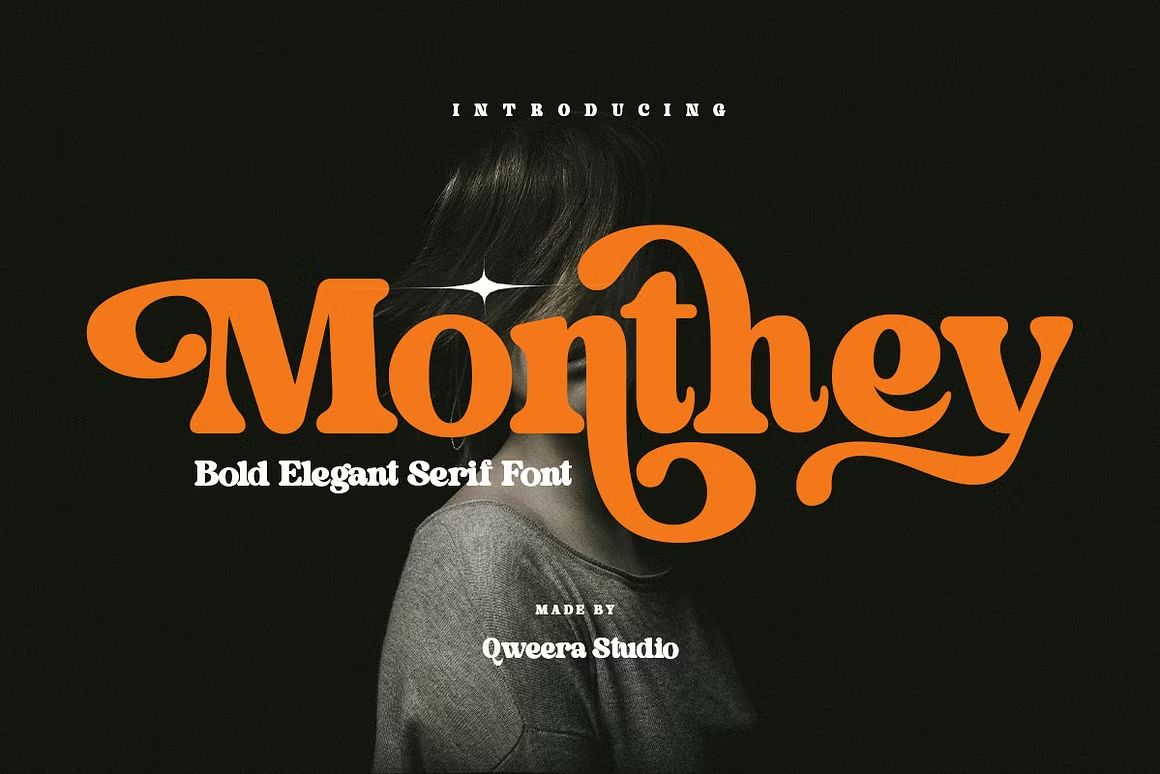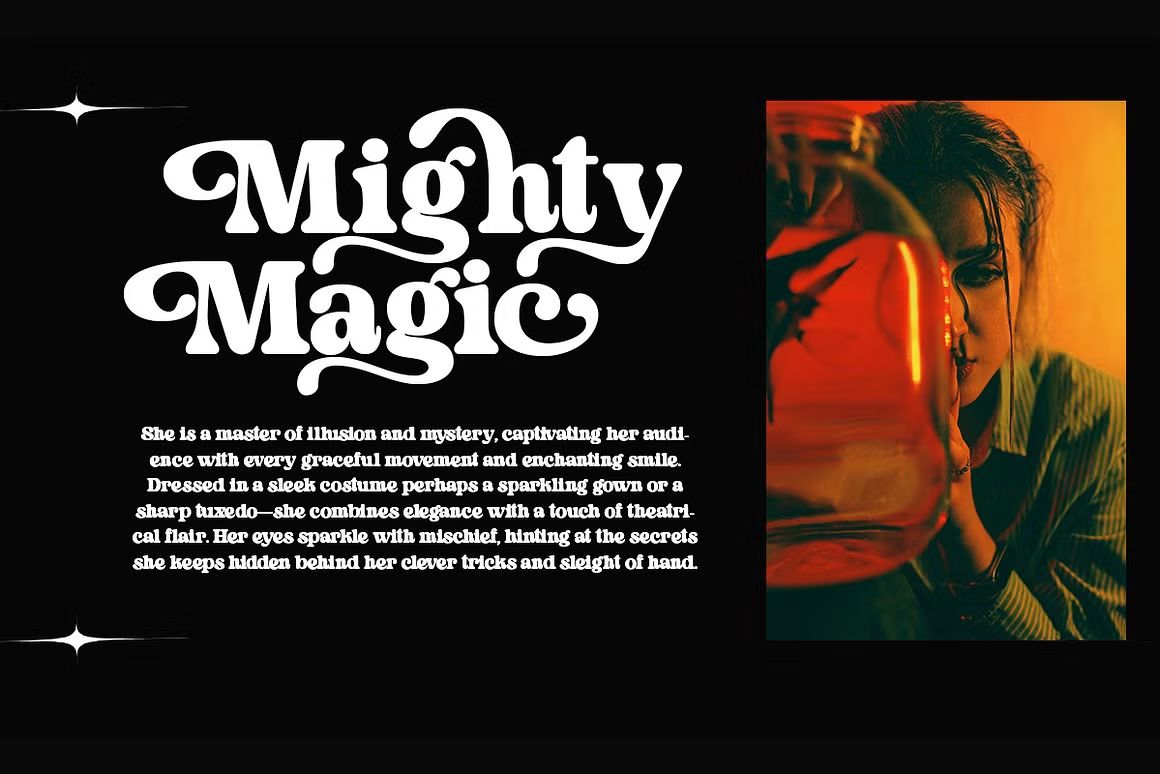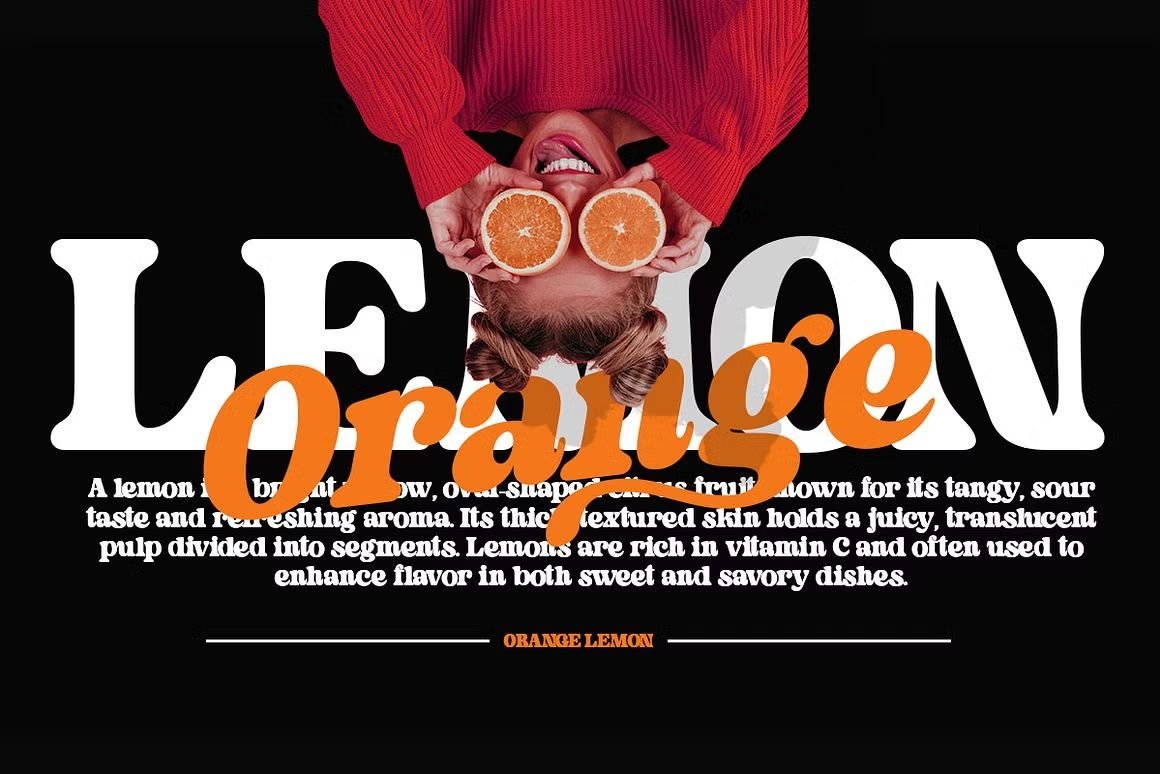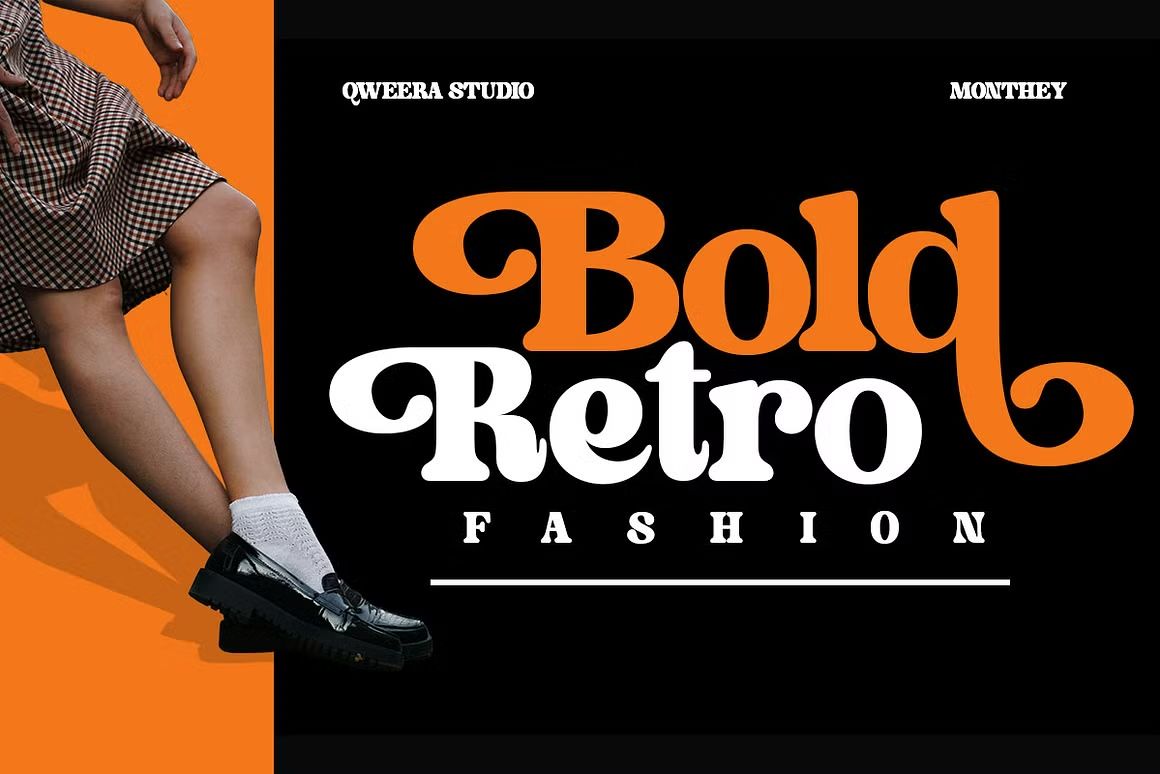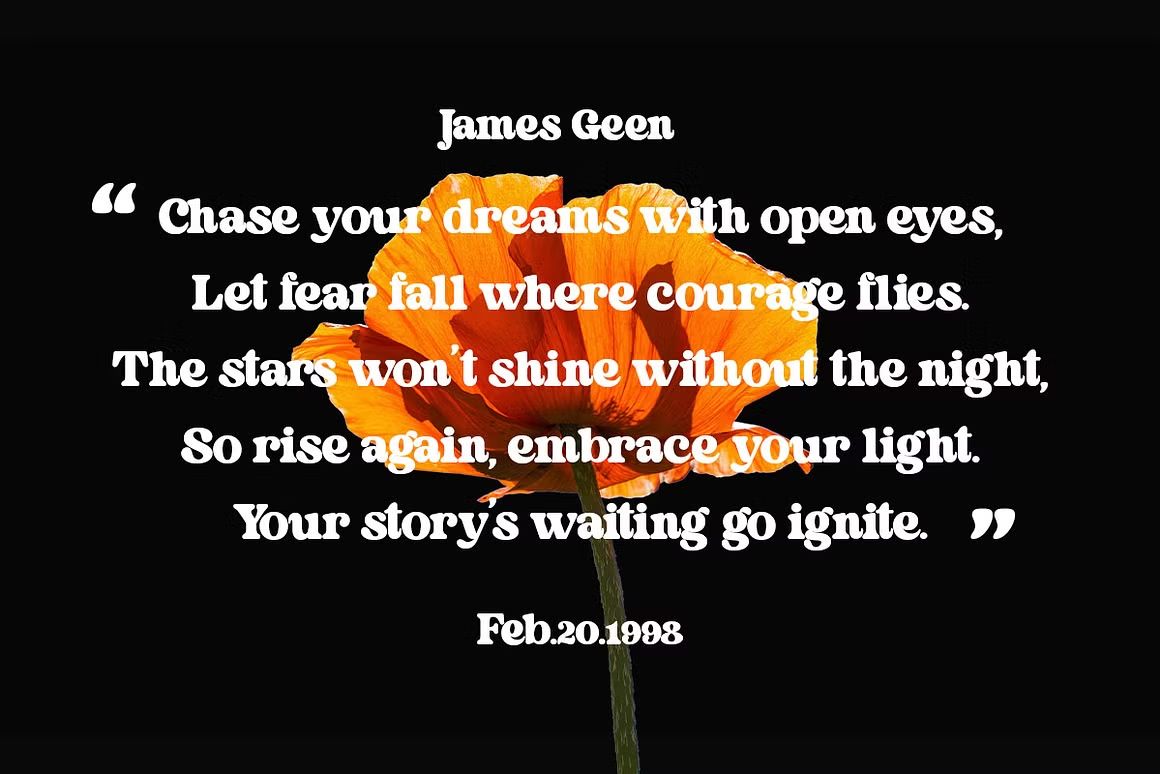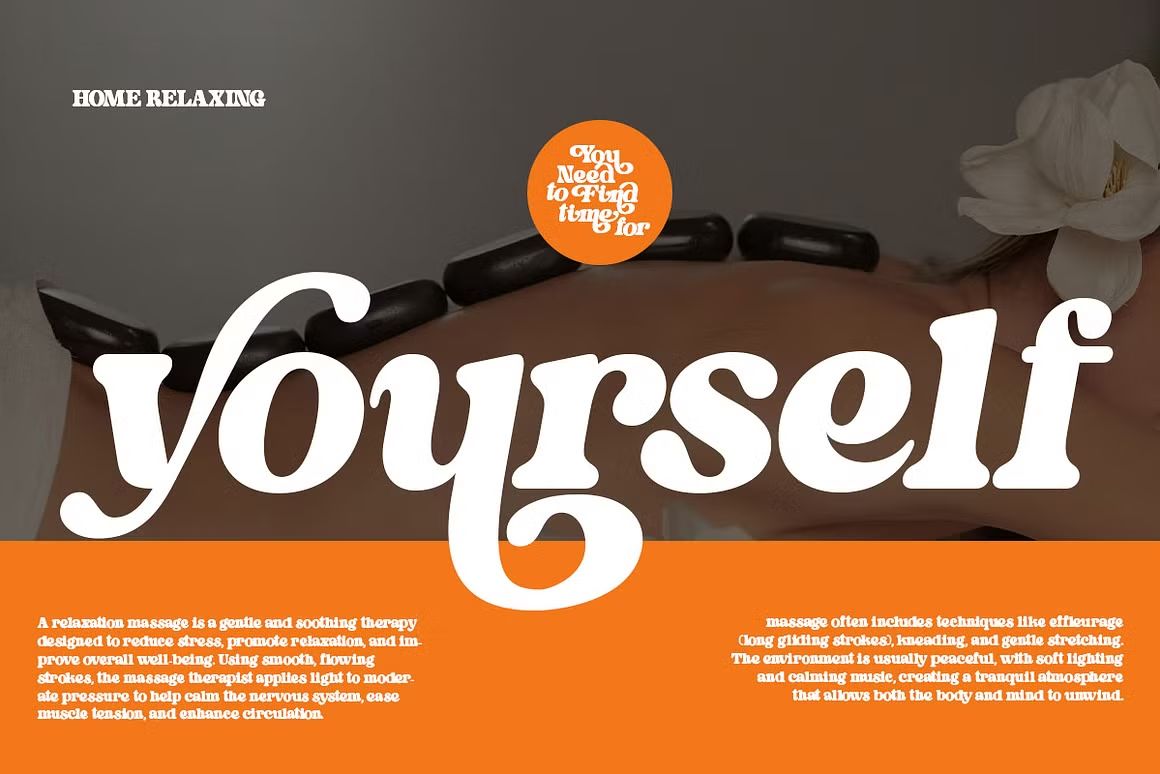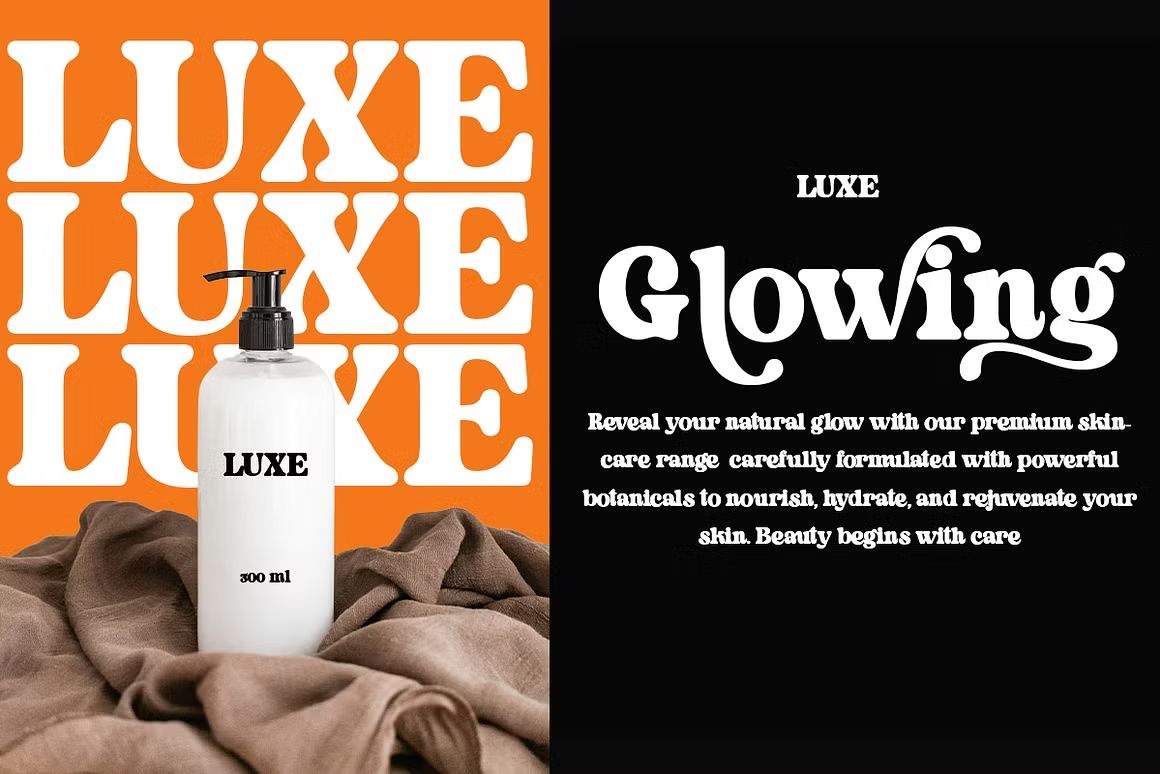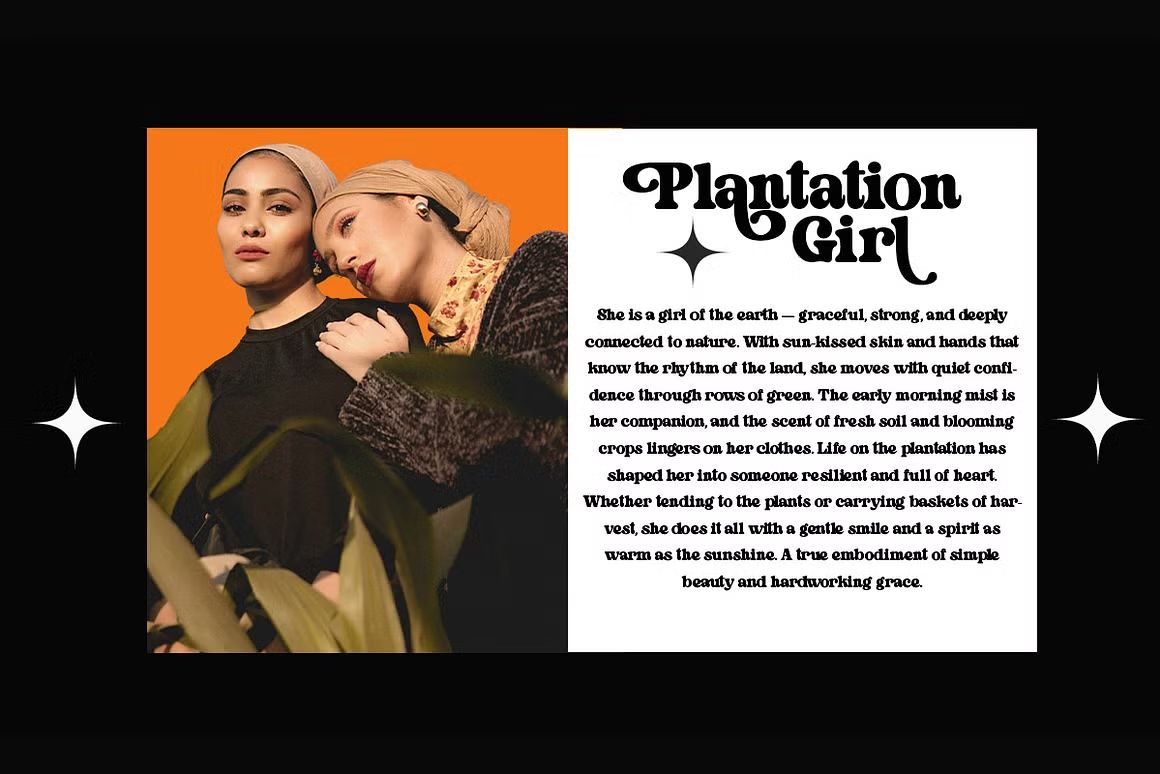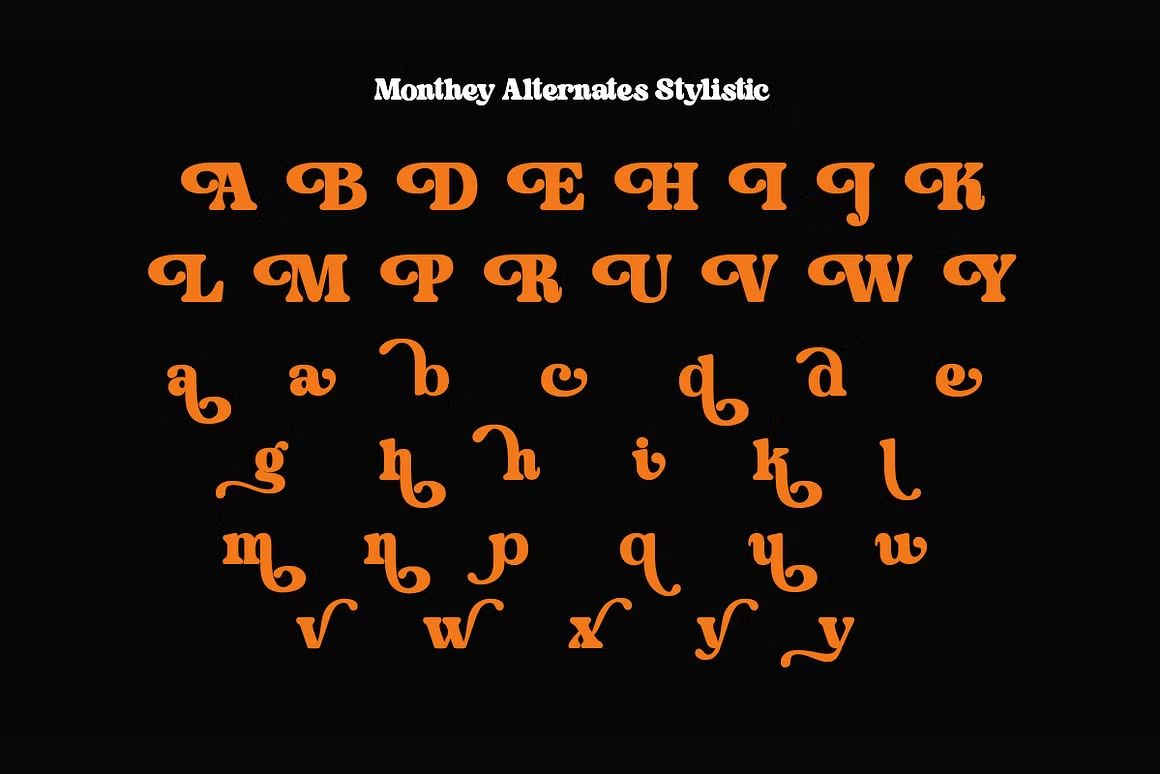
Monthey – Sans Serif Font
Monthey adalah font sans serif modern dengan desain bersih, tegas, dan profesional. Menampilkan bentuk huruf geometris yang proporsional dan mudah dibaca, font ini cocok untuk branding, editorial, presentasi bisnis, UI/UX, serta desain kemasan yang membutuhkan tampilan minimalis dan elegan. Monthey menghadirkan kesan kontemporer yang kuat dan fleksibel untuk berbagai proyek visual.
• Sans serif geometris dengan tampilan modern dan rapi
• Ideal untuk branding, desain digital, dan editorial profesional
• Termasuk huruf kapital, kecil, angka, dan simbol